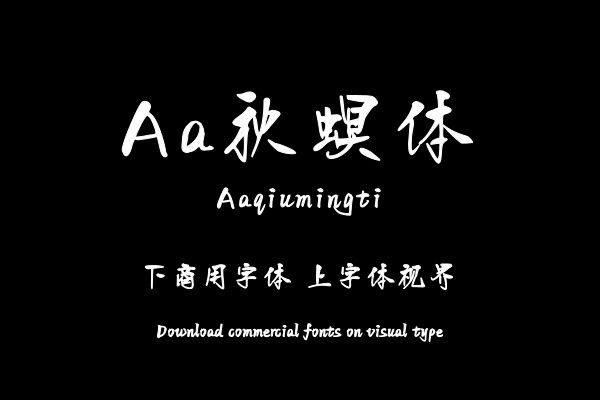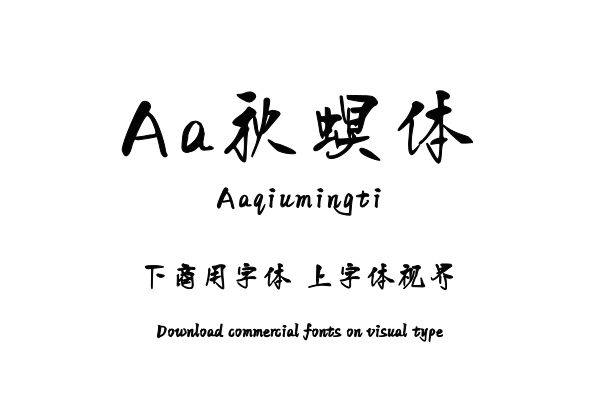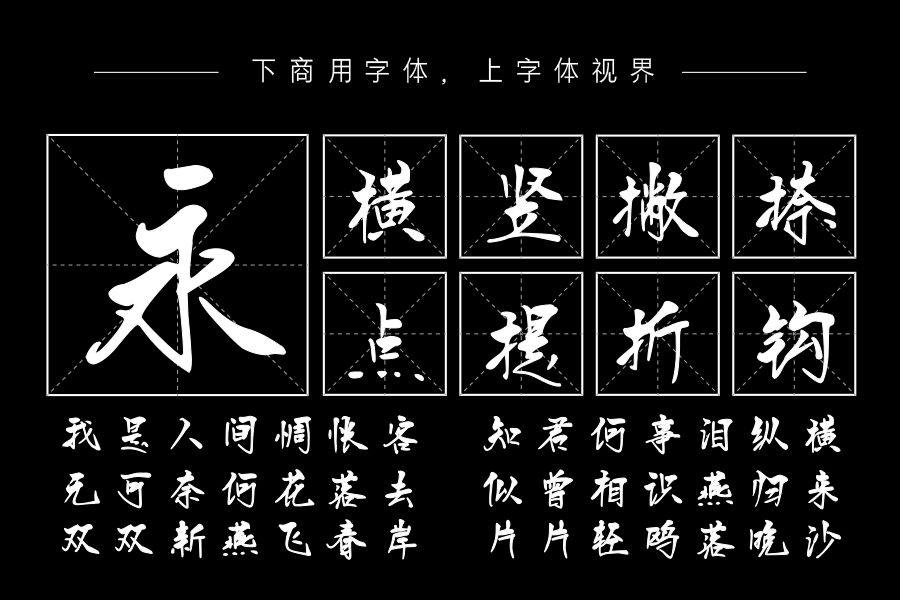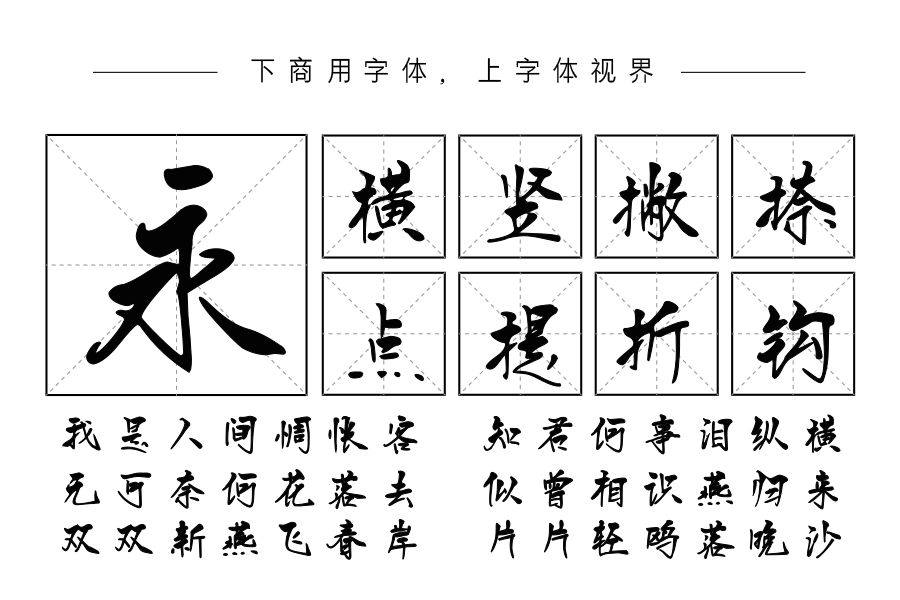
以特征性的手写方式提供全新的手写字体风格。上部的横相对厚重,竖向笔画越向下越尖锐纤巧,好似长腿小虫,优雅轻盈。购买须知:“下载服务费”与“字体VIP”所获得字体 仅用于个人非商用, 商用请联系付费授权。本字体为电脑用字,手机没有root权限不支持直接手机换字(手机如何root,请自行百度搜索教程)。购买前请先 了解清楚后再付款 ,字体为虚拟产品无法回收 一旦购买不支持退款。